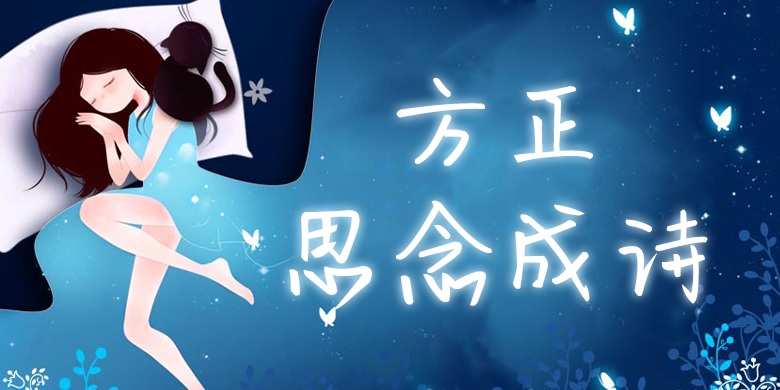
方正手迹-方正思念成诗
品牌:方正手迹设计师:郁沁蕾发行时间:2020字库编码:大陆简体(GB2312-80)分类:创意书写字体属性:精品字
方正思念成诗,其字整体上爽利洒脱,俊逸挺拔,但又不失稚拙的意趣。作者情之所致,流于笔端之真性情,使得该字增添了几许超然之气。适用于现代诗歌、短文的排版以及文化、商业类品牌的广告语设计。